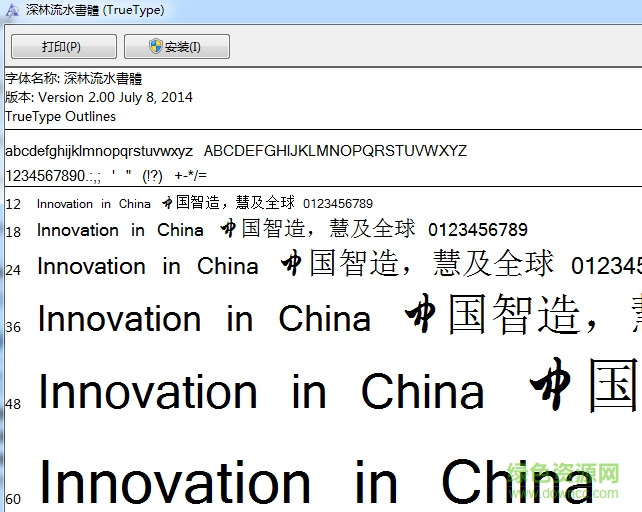
深林流水書字體是一款非常具有自己個(gè)性的字體,字庫(kù)中的字型非常瀟灑飄逸,讓用戶能夠在這款字體中看到一種意境,體會(huì)不一樣的感受,如果有喜歡這款字體的朋友,可以來(lái)綠色資源網(wǎng)免費(fèi)下載使用!
深林流水書字體是中文字體庫(kù)中的一款字體,字型瀟灑飄逸,效果顯著突出,帶給用戶別樣的體驗(yàn),有需要的朋友就趕快來(lái)綠色資源網(wǎng)下載吧!